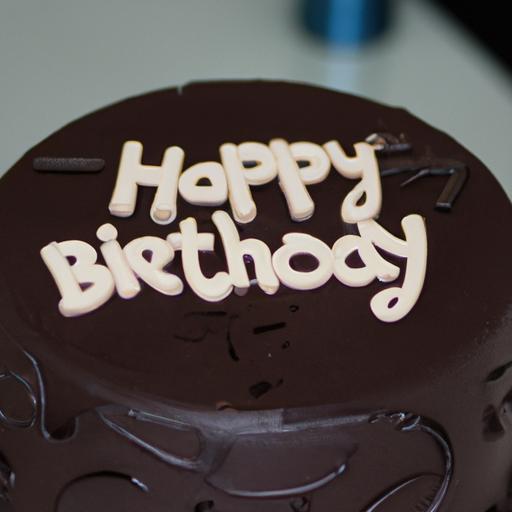
Font chữ happy birthday
Tác giả: Kimberly Geswain
Ngày phát hành: 2014
Ngôn ngữ: Tiếng Việt, nhiều ngôn ngữ khác
Bộ Font: Birthday Calligraphy
Phân loại: Vui nhộn, sinh nhật
Kiểu chữ: Script
Font chữ Happy Birthday thuộc bộ font chữ sự kiện là một trong những yếu tố quan trọng để tạo nên những tấm thiệp chúc mừng sinh nhật thật độc đáo và ấn tượng. Với các chữ happy birthday đẹp và phong cách, bạn có thể dễ dàng tạo ra những thông điệp sinh nhật vui nhộn và sáng tạo. Các mẫu chữ happy birthdayphông chữ happy birthday trong bộ sưu tập này được thiết kế để phù hợp với nhiều phong cách khác nhau, từ cổ điển đến hiện đại. Bài viết này sẽ giới thiệu 10 font chữ happy birthday đẹp nhất và cung cấp link tải miễn phí, giúp bạn dễ dàng chọn lựa và sử dụng.
Tổng hợp 10 font chữ Happy Birthday đẹp 2024
Các font chữ happy birthday được đề xuất đều có thiết kế đẹp mắt và dễ sử dụng, giúp bạn viết chữ happy birthday kiểu một cách dễ dàng. Những kiểu chữ happy birthday này không chỉ mang lại vẻ thẩm mỹ cao mà còn giúp thông điệp của bạn trở nên sinh động và hấp dẫn hơn.
Font chữ happy birthday VNI-Freewrite
Font UVF Kaileen
Font chữ happy birthday đẹp 2024 – UTM Dai Co Viet
SVN-Goldeye Type
Yellowtail – Font chữ Happy Birthday family
SVN-Marpesia Pro – Font chữ sinh nhật mềm mại
Font chữ Lazydog
Font chữ Happy Birthday – Font Playfair Display
Font chữ More Sugar
Font chữ Brasika